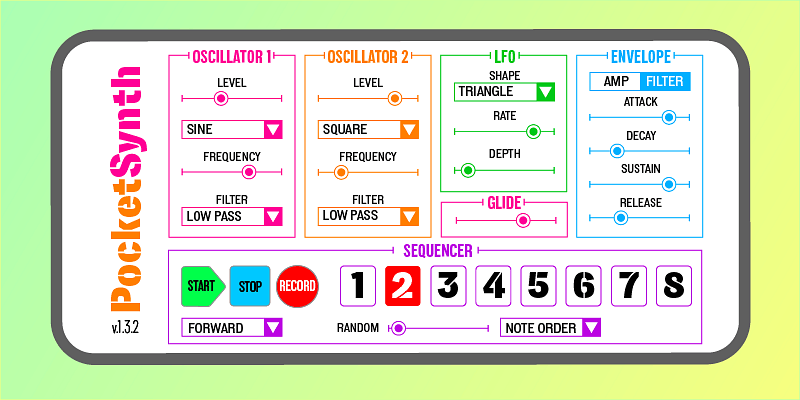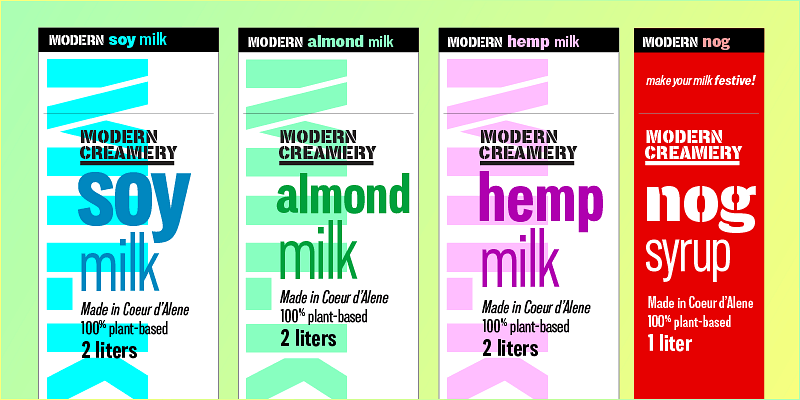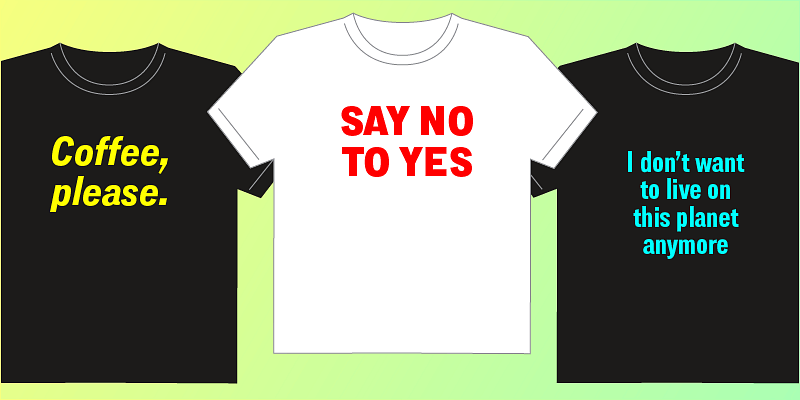
Lorimer No. 2는 카피라이터에게 개성을 부여한 1950년대 산세리프체 중 하나가 아닙니다. 박시한 곡선, 기울어진 터미널, 매력적인 x 높이는 이 산세리프체를 중립적이지 않게 만듭니다. 좁은 글자와 좁은 간격은 병이나 덮개와 같은 좁은 공간에 큰 이름을 넣고자 할 때 적합합니다. 두 가지 폭, 다섯 가지 두께 및 이탤릭체는 헤드라인에서 긴 카피에 이르기까지 다양한 작업에 적용됩니다. 또한 동반 제품인 스텐실 글꼴은 일치하는 디스플레이 서체를 제공합니다.